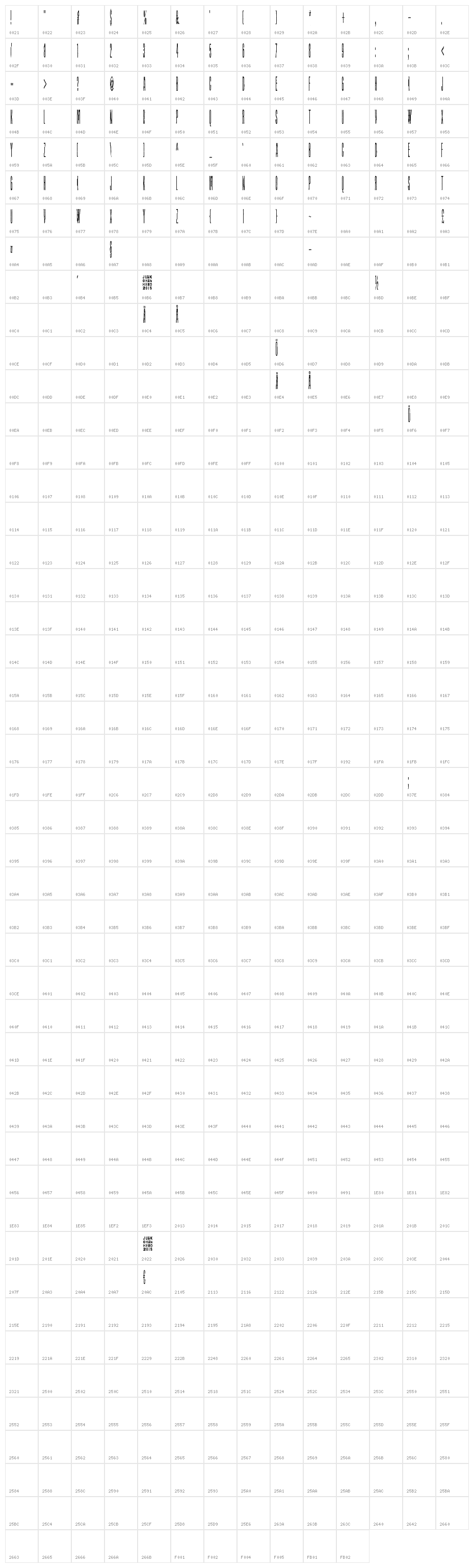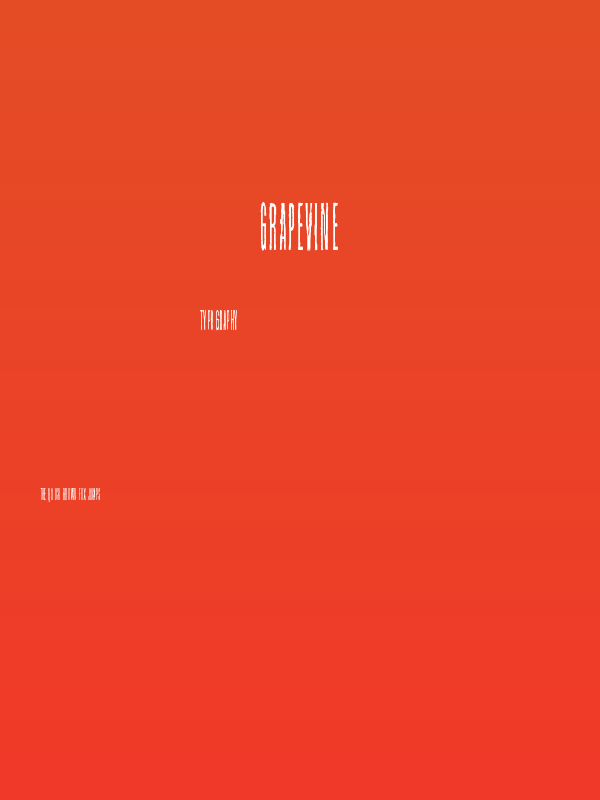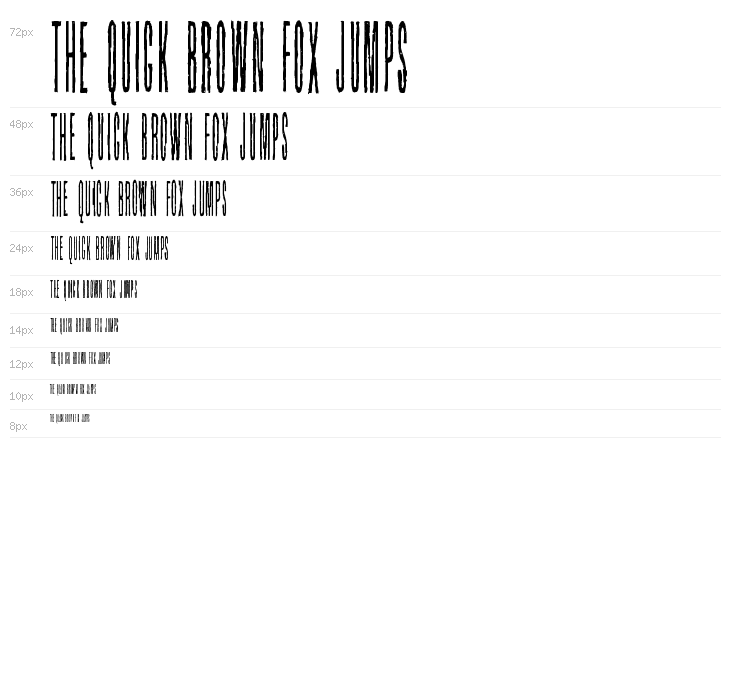
Grapevine Font
✎ Distorted Eroded
| Progetti proposti | Ideal for vintage-themed posters, rustic branding, packaging design, and creative projects that require a handcrafted look. |